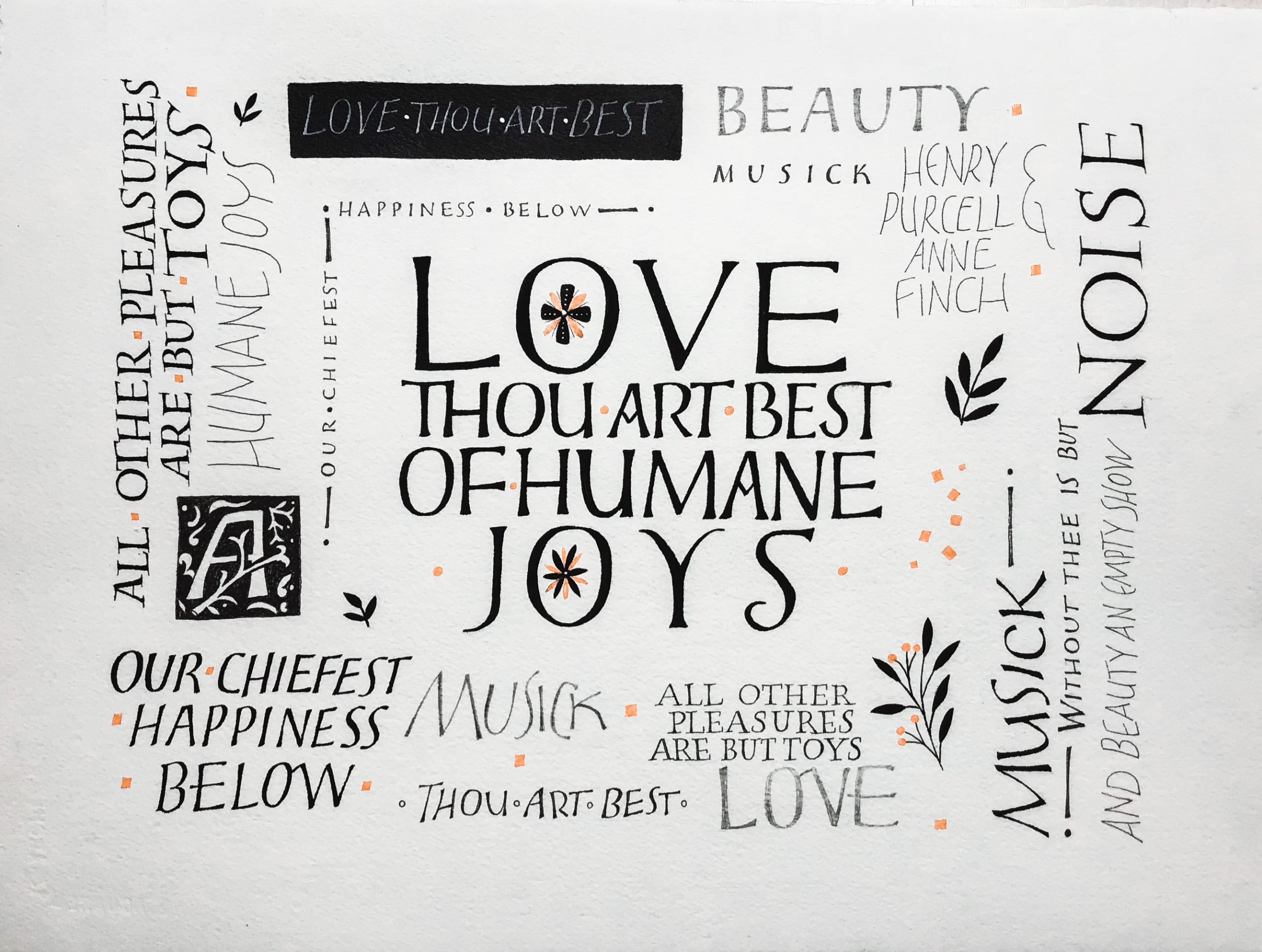
Depuis début mai, je suis le cours en ligne proposé par Yves Leterme sur le thème des capitales libres et dessinées : une approche à mi-chemin entre lettrage et calligraphie qui nous a emmenés sur une infinité de variations.
Nous sommes partis d’une capitale simple, tracée au porte-mine, puis nous l’avons étirée, compressée, engraissée, inclinée, courbée et ceci au crayon, au fineliner, à la plume, pour finir au pinceau (je n’ai pas encore commencé le pinceau, je redoute un peu).
C’est un travail de précision, de rigueur, d’observation mais aussi de grande liberté afin de produire quelque chose de dynamique et vivant. Nous nous sommes imprégnés du travail de David Jones, Liesbet Boudens, Ann Hechle, Kristoffel Boudens (entre autres) et avons pu découvrir les magnifiques carnets de Jurgen Vercaemst.
Capitale simple au crayon
Variations au crayon
Alphabets dessinés au crayon
Variations à la plume et au crayon
Inspiration des lettres de David Jones
Variations à la plume et au fineliner
Recherches en jouant sur tous les paramètres de la lettre
Variation au tire-ligne
Alphabet à la plume Speedball C4
J’avais envie depuis longtemps de travailler les lettres de cette manière et ce stage m’a ouvert de nouveaux horizons mais aussi une meilleure compréhension de ce qui fonctionne ou pas. C’est vraiment une question de design, de la lettre seule ou de son intégration dans un mot, une phrase.
1. Bravo Véro, pour toutes tes magnifiques planches ! J’adore particulièrement la noire et blanc avec des petits carrés rose saumon, trop chouette. Ce style de lettre est magnifique et en allant voir les profils instagram que tu conseilles, une question jaillit : comment pourrait-on faire pour utiliser ce style, sans que ça évoque immédiatement nos idoles de Belgique ? Comment le faire migrer vers son propre style ? Voilà un défi de taille ! Tu le relèves ? Bisous 😉
1. Ah voilà une remarque qu’elle est bonne : le style développé par les Boudens, David Jones et consorts est visuellement très fort et tout de suite remarquable. Pas facile de le faire migrer comme tu dis. Je crois que vraiment bien comprendre et savoir reproduire ces modèles est fondamental, c’est la base. Ensuite, Yves nous a donné toutes les clés pour travailler et effectivement développer quelque chose de personnel, s’envoler des modèles. C’est un travail de fond, de brouillons, d’essais, de ratages, de pages déchirées… Mais ça peut le faire si on y consacre le temps qu’il faut.
Une autre façon de faire, est d’intégrer ce savoir-faire dans le style de compos, couleurs, esprit de ce que l’on fait déjà 😉
A signaler aussi – entre autres calligraphes de grand talent participant à ce cours – le très beau travail de Katarina Ostenda (poesiederfeder sur instagram), Jasna Wittmann (jwkalligrafie) ou Sveta Suhova. Et bon courage pour la dernière semaine.
1. Oui !!! Nous étions cernés de grands talents, c’est génial. Pour la dernière semaine, le pinceau plat… gros challenge, je n’ai jamais fait !